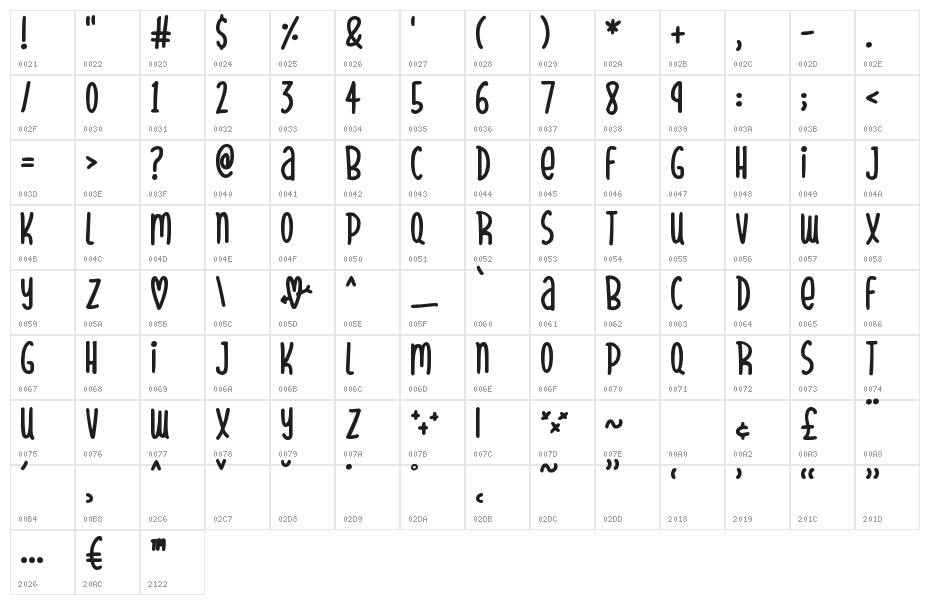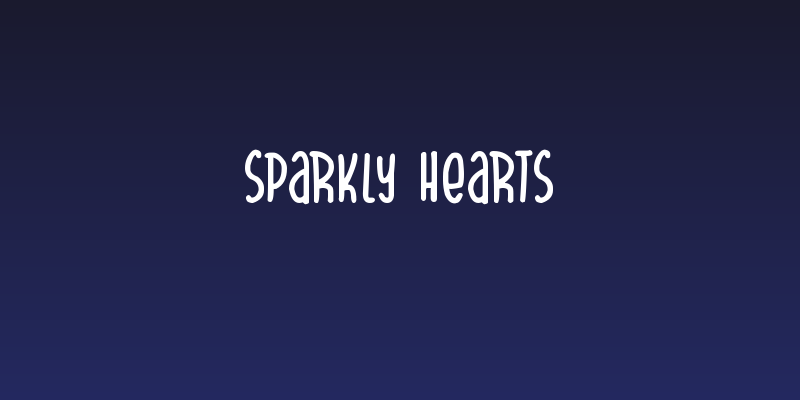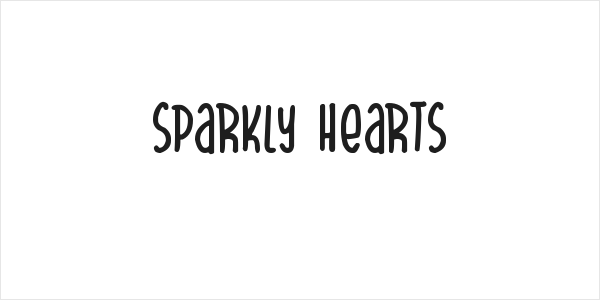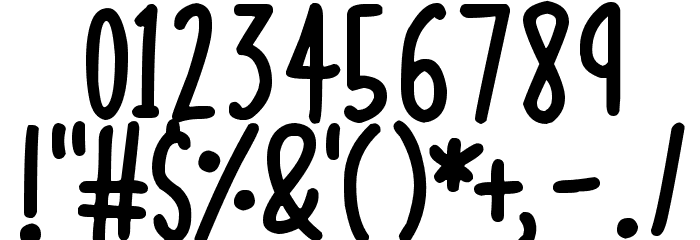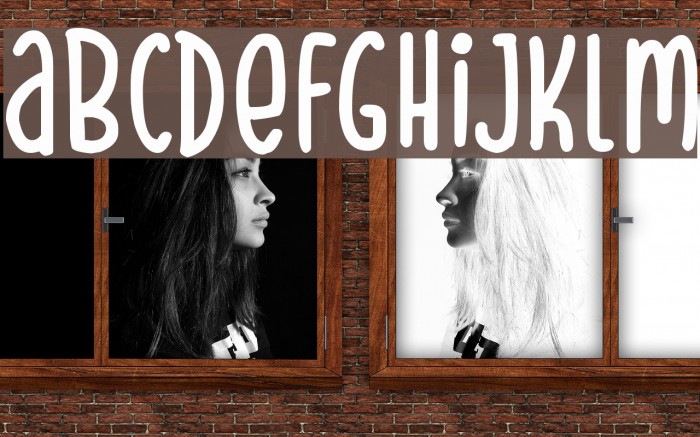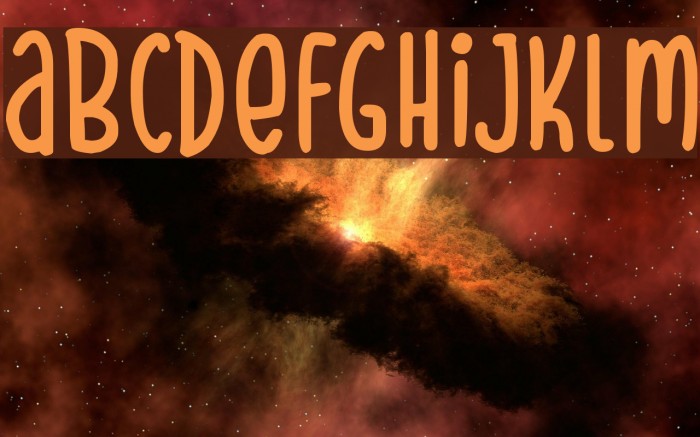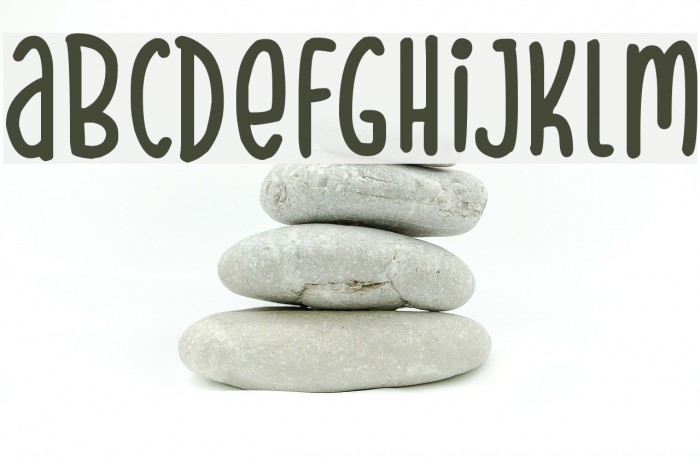
Sparkly Hearts Font
Darrell Flood
| Proyectos propuestos | Ideal for children's books, greeting cards, playful branding, and social media graphics. |